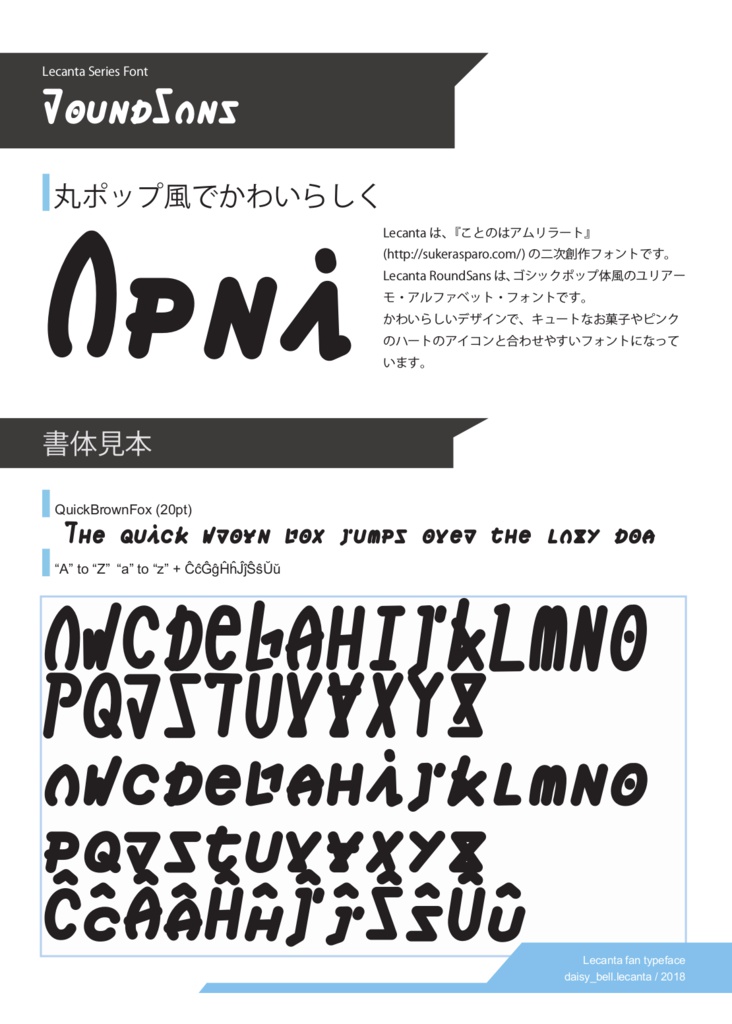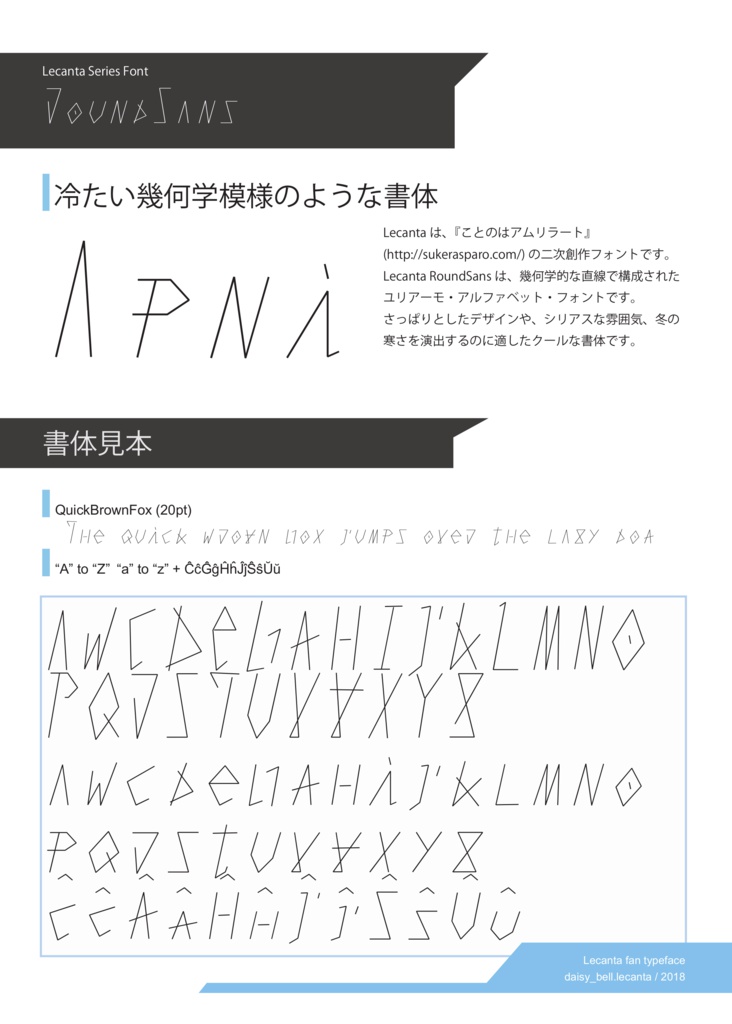
ファン創作 ユリアーモ文字 フォント集 (筆記体フォント+)
Lecantaは、[ことのはアムリラート]( http://sukerasparo.com/ )のファン創作フォントです。 劇中に登場する架空言語ユリアーモを表記する際に使われる、ユリアーモ・アルファベット(仮称)を元にデザインされています。 - Lecanta ScriptManeuvers:筆記体 - Lecanta RoundSans:丸ポップ風サンセリフ体 のユリアーモ・アルファベット・フォントを収録しています。 [github]( https://github.com/MichinariNukazawa/Lecanta_Series_Fonts/releases/ ) からもダウンロード可能です。 2018/06/24:新書体PopScript追加